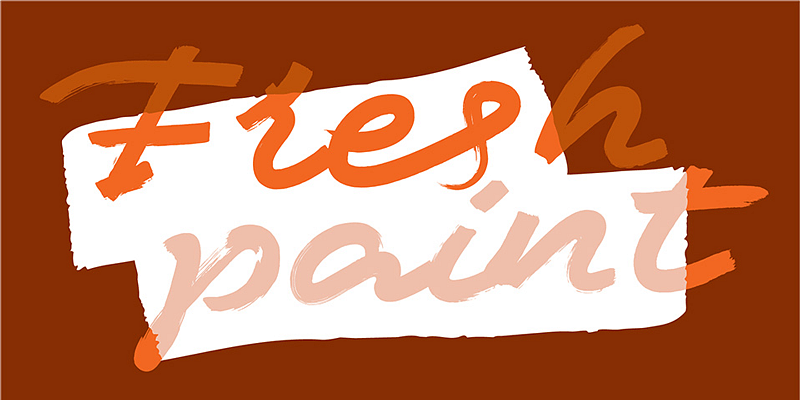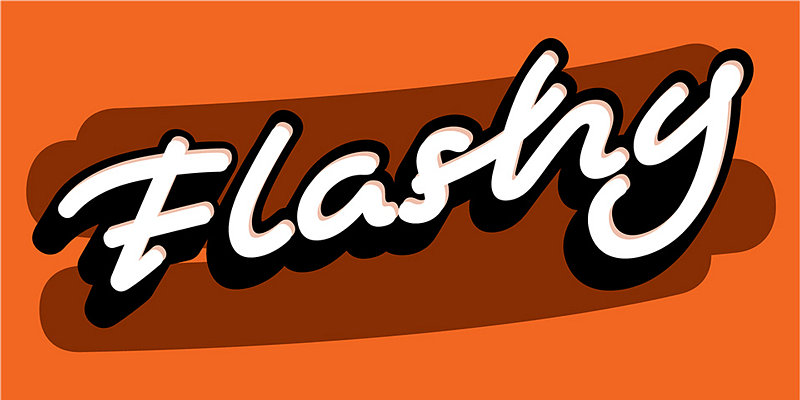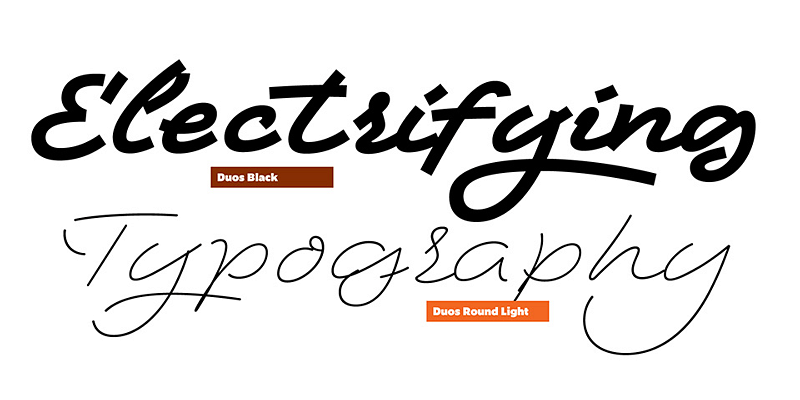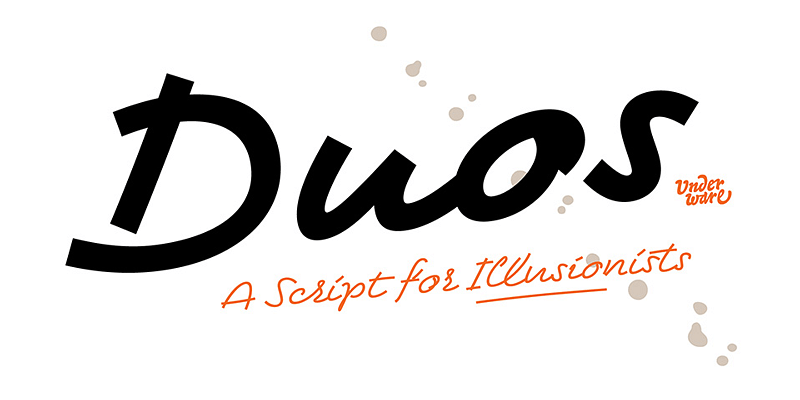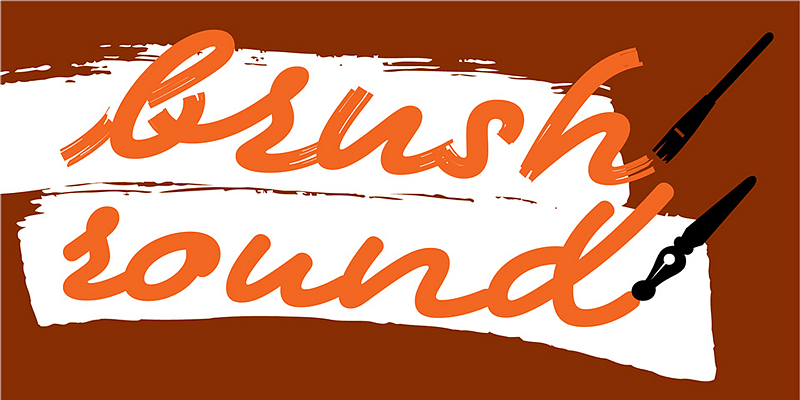
Duos, uno script per illusionisti, è disponibile in 10 stili. Qualunque sia lo stile che scegli, applica questo font di scrittura monolineare veloce in grandi dimensioni, perché è fatto per catturare l’attenzione.